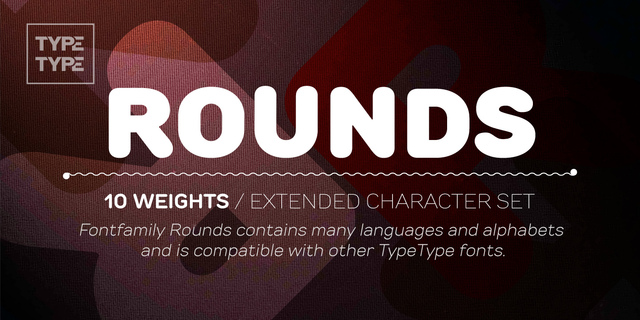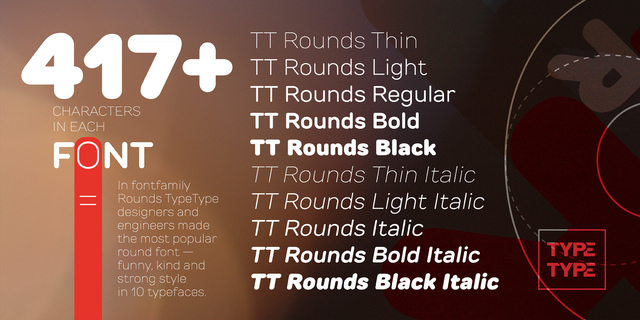
Rounds – шрифт с очень добрым и нежным характером. Самый популярный набор начертаний: тонкое, светлое, нормальное, жирное, сверхжирное и их наклонные версии. Шрифт сделан таким образом, чтобы он мог применяться как в кратких текстах (логотип или заголовок), так и в полосе набора (абзац текста или статья в газете). Область применения: детские книжки, кафе, упаковка, сайты, ценники, логотипы, реклама, косметика, игрушки. Оптимизирован для применения на сайтах, в мобильных приложениях и печатной продукции. Шрифт разработан Иваном Гладких в студии TypeType Fonts в 2014 году.
Асоціації з сімейством шрифтів TT RoundsОсобистість і характер гарнітури:
делікатний, чистий, легкий, прохолодний, свіжий, модний, тонкий, сучасний, лаконічний, ясний, рівний, якісний, невагомий, прозорий, інтимний, точний, акуратний, логічний, ніжний, повітряний, дротяний, худий, неоновий, міський, зрозумілий, приємний, М'який, симпатичний, мирний, комфортний, бадьорий, Простий, зручний, домашній, добрий, привітний, дитячий, милий, пишний, спокійний, доброзичливий, затишний, гладенький, пластмасовий, сімейний, смачний, наївний, важкий, масивний, товстий, пухкий, сильний, апетитний, потужний, помітний, яскравий, активний, гумовий
лосьйон, краса, туалетна вода, шампунь, косметика, мода, дієта, чистота, гігієна, девайс, гаджет, інженер, креслення, технології, АСМР, вода, прилад, Місто, інтер'єр, йога, небо, ліки, здоров'я, мобільний зв'язок, спальня, дім, молоко, дитяче харчування, розфарбування, їжа, торгівля, кондитерська, солодощі, випічка, булочна, кафе, родина, іграшка, булочки, булочка, десерт, латте, мафін, смузі, гра, м'яка іграшка, сік, дитяча книжка, шоу, телебачення, сир, соус, сметана, кетчуп, подушка Гарнітура має ознаки стилів:
— Гарнітура асоціюється з віком: